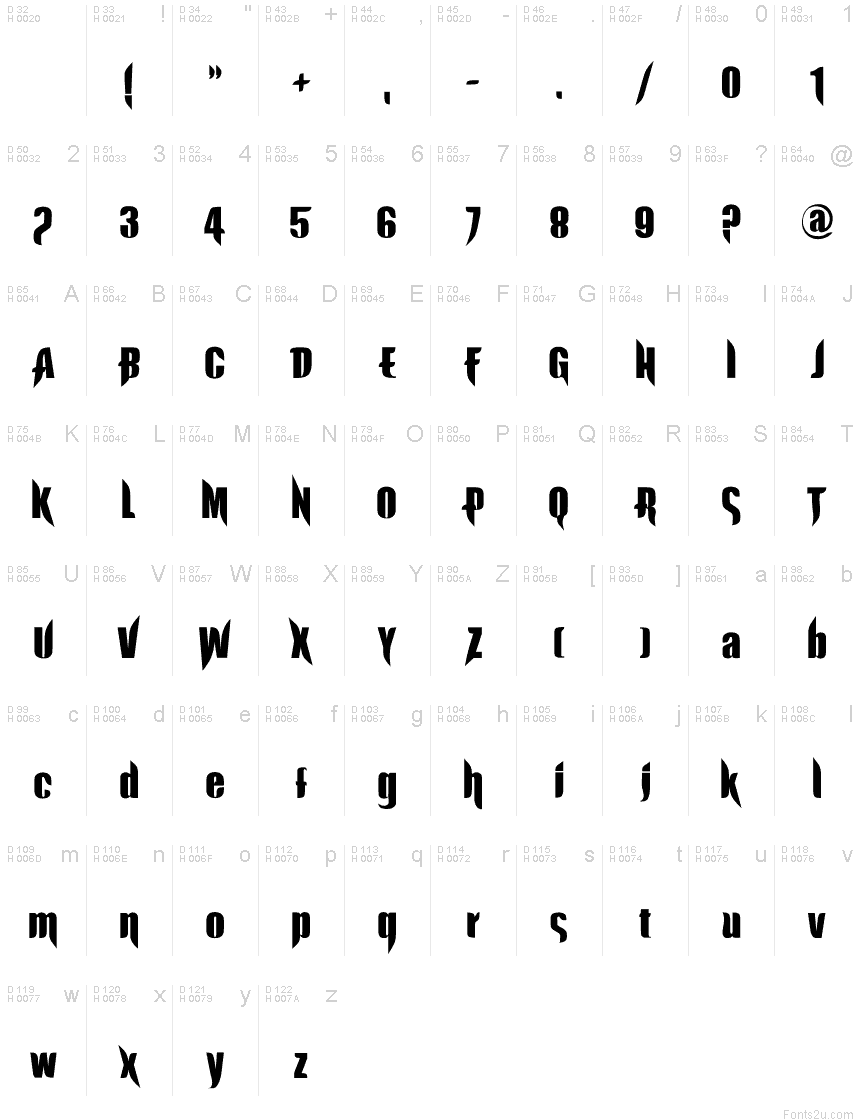
Exorsista Jed è un font gotico moderno e gratuito dal tratto affilato e teatrale. Le lettere mescolano masse scure e pesanti con tagli netti come lame e curve a uncino, creando un effetto drammatico e quasi cerimoniale, ben lontano dalle atmosfere medievali polverose.
È perfetta per poster, branding horror, copertine di album, flyer di eventi e titoli che richiedono quell'atmosfera tesa e rituale. Essendo un font gratuito, funziona benissimo anche per loghi, incipit di capitoli e brevi scritte su packaging: le giunture sezionate e le forme piene donano alle parole brevi una presenza deliberata e quasi iconica.